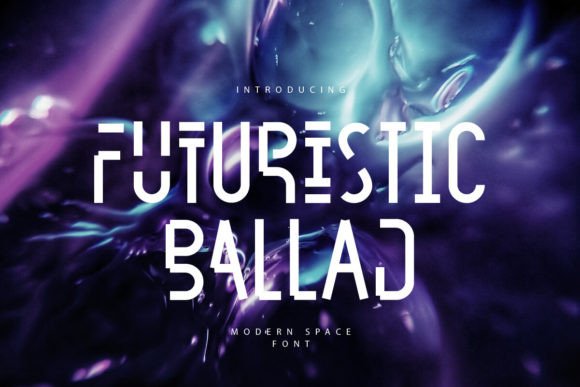
Futuristic Ballad
Futuristic Ballad – A Fonte Moderna que Transforma Seu Projeto
Se você procura uma tipografia que una estilo futurista e elegância clássica, Futuristic Ballad é a escolha ideal. Desenvolvida para atender às demandas de design de tecnologia avançada, branding, logotipos, pôsteres e embalagens, esta fonte traz uma presença visual impactante que destaca sua marca no mercado.
- Variedade completa de caracteres: inclui letras maiúsculas e minúsculas, números, sinais de pontuação, além de suporte a caracteres cirílicos.
- Conjunto alternativo: versões latinas e cirílicas alternativas para ampliar a criatividade tipográfica.
- Ligaduras avançadas: garante transições suaves entre letras, perfeito para títulos e cabeçalhos de alto impacto.
- Suporte multilíngue: ideal para projetos globais que exigem consistência visual em diferentes idiomas.
- Versatilidade de uso: funciona perfeitamente em projetos de tecnologia, identidade visual, materiais de marketing e design de produto.